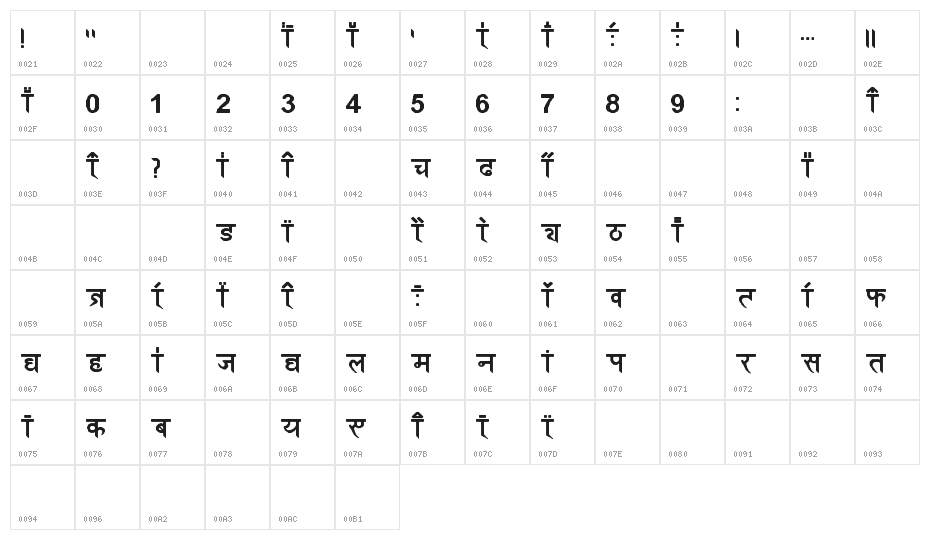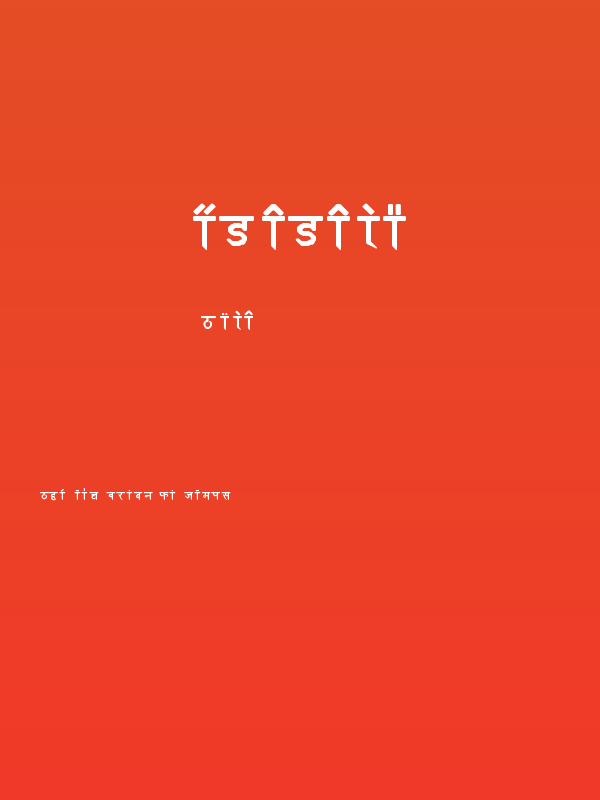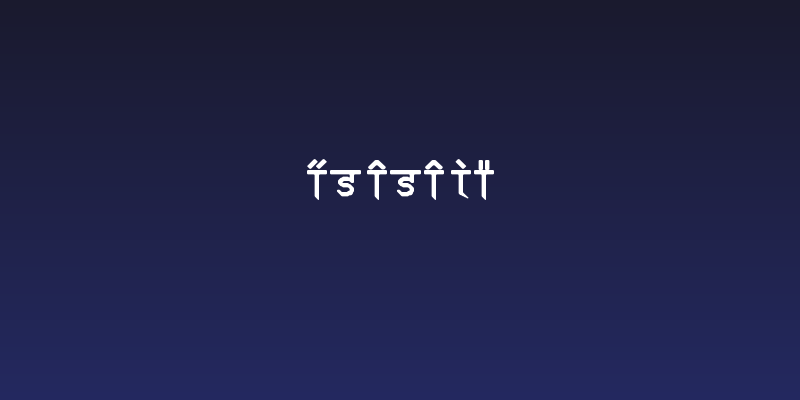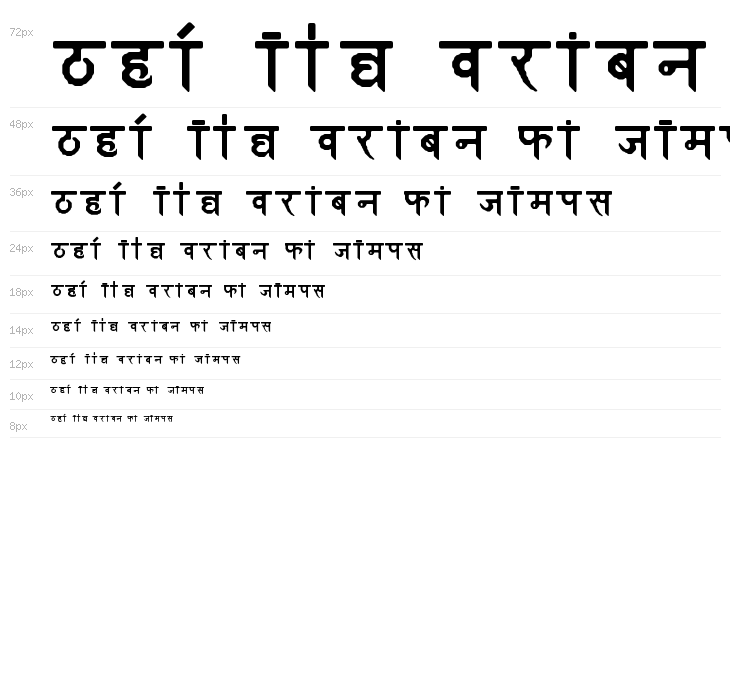
Enganagri Font
| Vorgeschlagene Projekte | Ideal for cultural or historical projects, artistic posters, branding that requires a traditional touch, and decorative headings. |